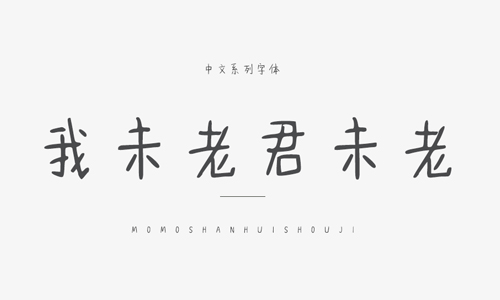
我未老君未老字体是一款有些可爱且随意的手写风格字体,世界上最美好的事情,就是和你一起走在路上,我未老,君亦未老。——我未老君未老,可以应用于广告海报设计等领域,本字体是在国家标准简体字库GB2312所包含6763汉字的基础上,又增加了近200常用字,已经覆盖了大陆99.75%的汉字使用频率,足以满足日常需求。欢迎大家前来下载。